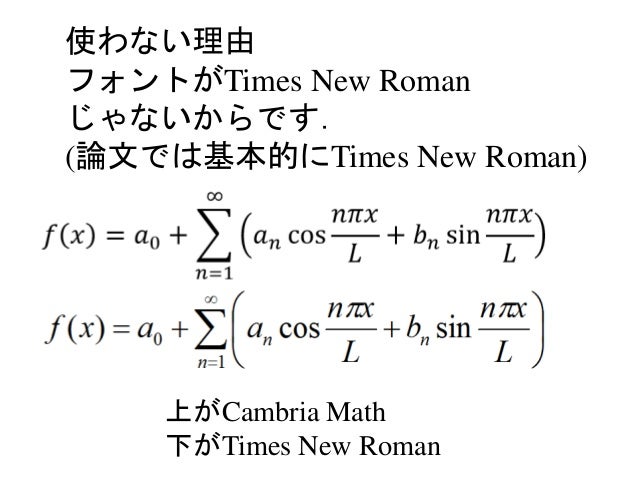
Word フォント おすすめ 論文
はLaTeX風のフォントでやや細めであり,少々違和感があるか もしれません.MS-Word のTimes フォントセットに近い “XITS Math”を使うこともできま す.下記のサイトより,XITS Math フォントをダウンロードしてインストールしてください..
Word フォント おすすめ 論文. どのフォントも可読性に優れており、 遠目にも非常に読みやすい ことが特徴です。 海外の大学に通っていた時、授業課題などの提出物は「このフォントで」と教授にフォントを指定されていたのですが、ほとんどの場合、指定フォントは Arial でした。. - 1 - 技術文書のためのWordの使い方 Usage of Word for Technical Writing 電子情報工学科 藤田 悠 1. こんばんは。初めて投稿します。 現在、大学で日本語の論文を書いています。 フォントは大学で指定された通りMS明朝で書き進めているのですが、 最初文章を書き始める際は半角英数で入力するとき、Centuryにフォントが自動変換されるため問題ないのですが、 途中で一度、文章全体を選択し.
論文では、様々な属に属する種について論じることがあるかもしれません。Solanum tuberosum (ジャガイモ) とSorghum bicolor (モロコシ、キビ)のように、偶然イニシャルが同じになる属もあるでしょう。. 本文のフォントサイズは英文であれば11から12ポイント、 日本語であれば10から11ポイントとする。 (引用元: 論文/レポートを提出する学生のみなさんへ|早稲田大学法学部教授 言語学/認知科学博士 北原真冬 ). ぜいたく 論文 フォント おすすめ.
フォントは論文全体を通して同じものを使用すること。異なるフォントを混ぜないこと。 明瞭で判読しやすいフォントを利用すること。Times New Romanの12ポイントが望ましい。 本文の行間はダブルスペースにする。 白の背景に黒字を使用する。. Symbolは、一般的なフォントで、全世界共通で使えます。 投稿論文(Natureとか)のギリシャ文字や記号の入力にも使われる フォントです。 文字化けが起こらないので、安心して使えますね! 3. Office Word®のデフォルトの半角英数字用フォントはCenturyです。ただ理系の方はとくに論文や学会の要旨を書くときにTimes New Romanを使うといいと教わるか,先輩の資料がそうなっているからそのまま真似るかしていると思います。.